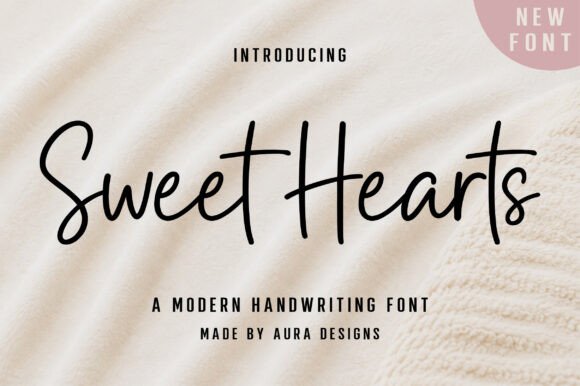
Sweet Hearts
์ •๋ฐ€ํ•˜๊ฒŒ ์ œ์ž‘๋œ Sweet Hearts๋Š” ๊น”๋”ํ•œ ๋ฒกํ„ฐ, ๋ถ€๋“œ๋Ÿฌ์šด ํƒ€์ดํฌ๊ทธ๋ž˜ํ”ผ ๋ฐ ์•ˆ์‹ฌํ•  ์ˆ˜ ์žˆ๋Š” ์ƒ์—…์šฉ ๋ผ์ด์„ ์Šค๋ฅผ ์ œ๊ณตํ•ฉ๋‹ˆ๋‹ค.
POD(์ฃผ๋ฌธํ˜• ์ธ์‡„) ์ œํ’ˆ, ๊ฒฐํ˜ผ์‹ ์ดˆ๋Œ€์žฅ ๋˜๋Š” ์†Œ์…œ ๋ฏธ๋””์–ด ๊ทธ๋ž˜ํ”ฝ์„ ๋งŒ๋“ค ๋•Œ Sweet Hearts๋Š” ์ด์ƒ์ ์ธ ์„ ํƒ์ž…๋‹ˆ๋‹ค.